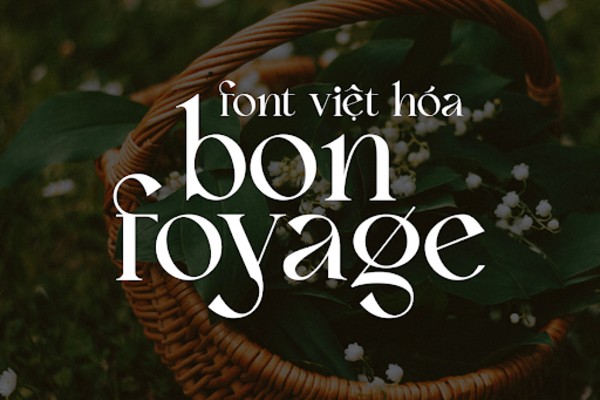
Tính đến thời điểm này đã có rất nhiều font chữ khác nhau được ra đời, nhưng không phải font chữ nào cũng có khả năng hiển thị tốt với tiếng Việt. Nếu bạn sử dụng sai font chữ hoặc những font chữ chưa được việt hóa thì sẽ gây ảnh hưởng đến sản phẩm của bạn. Hãy cùng chúng tôi tìm hiểu chi tiết về Font chữ việt hóa là gì và top 7 font việt hóa đẹp qua bài viết dưới đây nhé!
Font chữ việt hóa là gì?
Như chúng ta đã biết hiện nay trên thế giới có vô số các font chữ khác nhau, do mỗi quốc gia tự đưa ra và tất nhiên nó chỉ hỗ trợ tốt nhất cho ngôn ngữ của quốc gia họ. Chính vì thế không phải font chữ nào cũng có thể dùng tiếng Việt. Và nếu bạn muốn sử dụng font chữ đó cho tiếng Việt thì bạn cần phải trải qua quá trình việt hóa font chữ.
Bạn có thể hiệu một cách đơn giản, font chữ việt hóa chính là sự chuyển đổi từ font chữ nước ngoài vốn không hiển thị tốt đối với ngôn ngữ tiếng Việt sang hiển thị một cách rõ ràng và tốt hơn.
Font chữ bắt nguồn từ đâu?
Font chữ được bắt nguồn từ đâu? Đây là từ được bắt nguồn từ tiếng Pháp “fonte”. Khi mà ngành công nghiệp in ấn ngày càng phát triển tại Pháp người ta đã sử dụng các khuôn đúc có sẵn từng ký tự của văn bản. Khi sử dụng để in, người ta thường sắp xếp các ký tự này thành các khối văn bản cụ thể. Lúc này các font chữ thường có kích thước và hình dáng thống nhất. Kể từ khi được du nhập về Việt Nam cùng với đó sự phát triển của chữ quốc ngữ, chúng đã được sử dụng nhiều hơn. Tuy nhiên do nhiều nguyên nhân font chữ đã được Việt hóa thành phông chữ.
Với sự bùng nổ của khoa học công nghệ, con người đã tạo nên vô số các font chữ khác nhau cho nhiều ngôn ngữ khác nhau. Những font chữ tiếng anh có sẵn được chỉnh sửa và thêm thắt dấu, ký tự để có thể soạn thảo văn bản tiếng Việt, và đó được gọi là font chữ việt hóa. Những font chữ này được nghiên cứu dành riêng cho tiếng Việt. Nhưng người ta thường hay gọi chung là các font chữ đó là font chữ tiếng Việt hoặc là font chữ việt hóa.
Tác hại của việc không sử dụng font chữ việt hóa cho tiếng Việt
Do cấu trúc bảng chữ cái của từng ngôn ngữ khác nhau, vì vậy việc sử dụng font chữ nước ngoài để hiểu thị các văn bản tiếng việt sẽ gây ra rất nhiều lỗi và đó được gọi là lỗi font. Nguyên nhân là do những font chữ này không thể tìm thấy ký tự phù hợp với những ký tự có dấu của tiếng Việt ( kí tự có dấu – một trong những nguyên nhân gây lỗi font thường thấy nhất). Vì vậy chúng sẽ tự động tìm và gán ký tự bất kỳ thay thế cho ký tự không được tìm thấy.
Đặc biệt là khi thiết kế việc sử dụng của font chữ không được rõ ràng sẽ làm cho nội dung hiển thị bị kém, người xem có thể đọc được nội dung hoặc đọc nhầm nội dung. Dẫn đến việc sản phẩm thiết kế không đạt được hiệu quả tốt, thậm chí là gây hiểu nhầm cho người đọc và dẫn đến sự phản đối từ xã hội hoặc cộng đồng.
Đối với văn bản pháp luật, cần tránh tình trạng lỗi font chữ do tính chất nghiêm tú, minh bạch và rõ ràng của loại văn bản này. Nếu một văn bản bị lỗi font chữ sẽ không thể đọc được chính xác và rõ ràng ý nghĩa của nó, vậy nên văn bản đó không có hiệu lực.
Vì thế, hãy sử dụng những font chữ đã được việt hóa, giúp văn bản và nội dung của bạn trở nên dễ hiểu và được hiển thị một cách tốt nhất đối với người đọc.